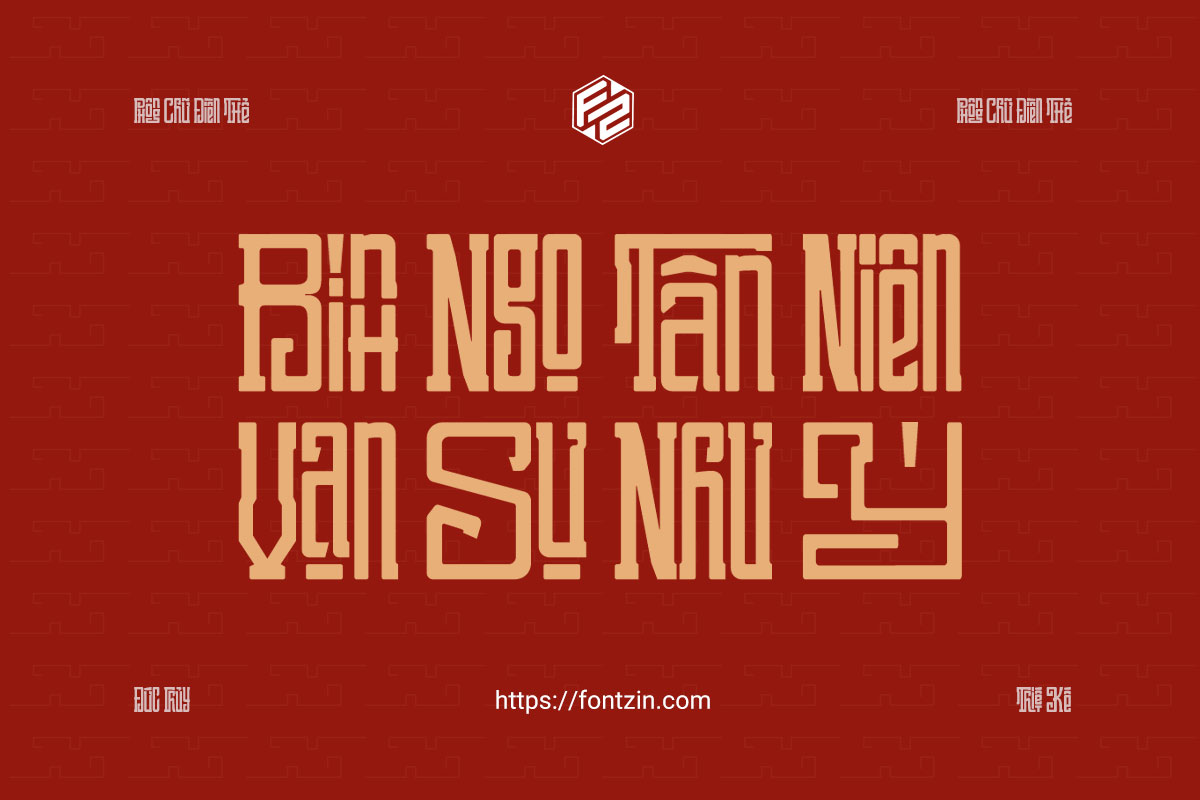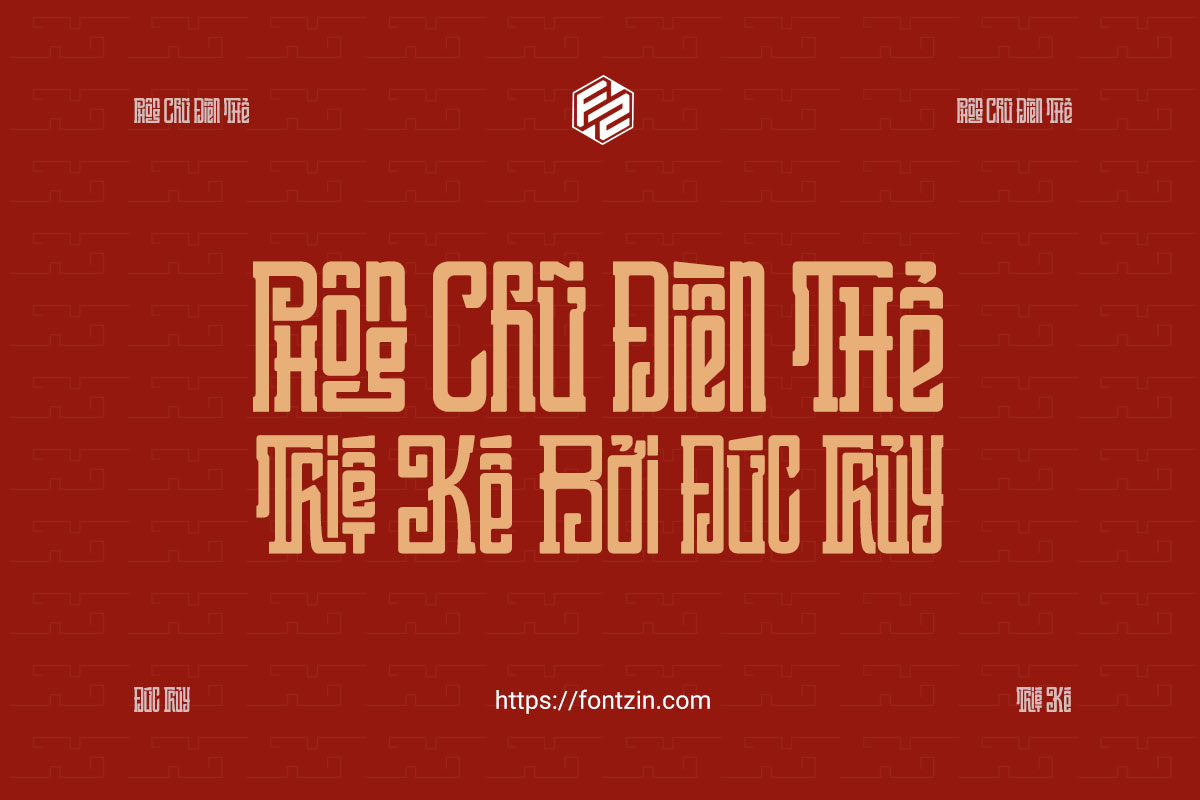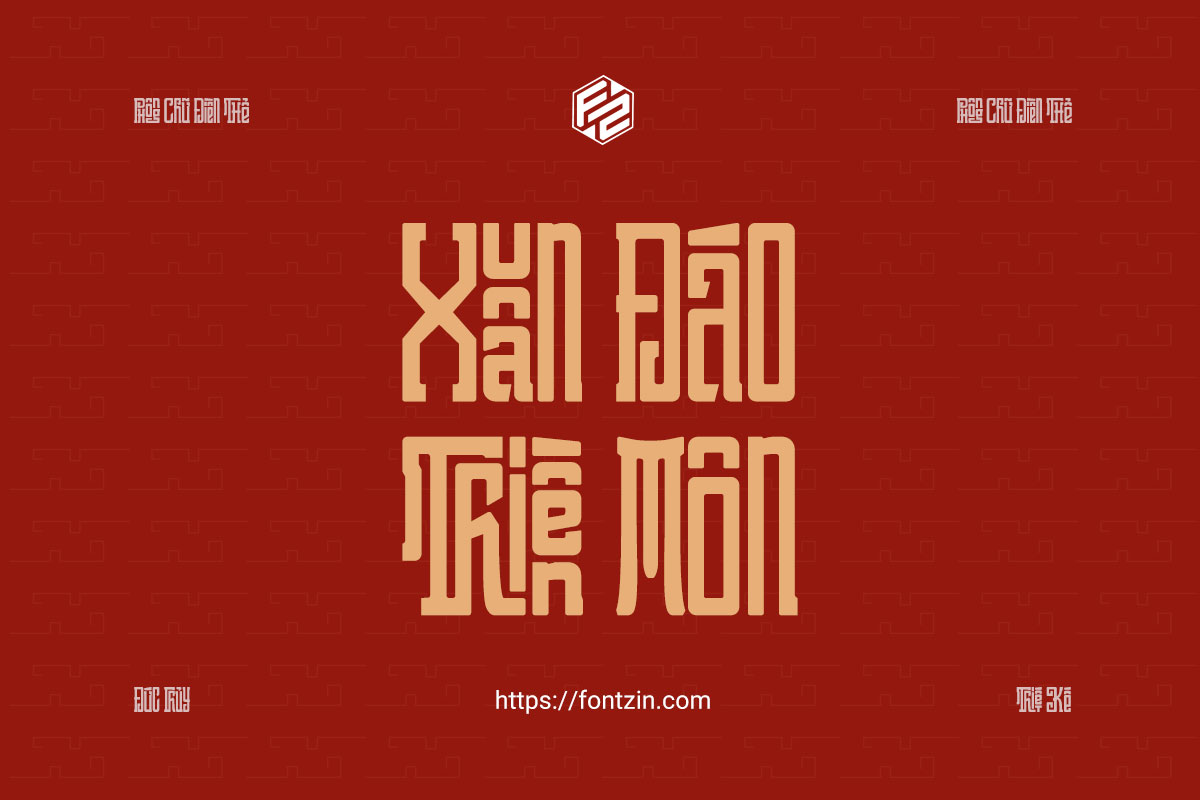
Font Điền Thể V8 (Font Triện) bao gồm gần 10.000 chữ Tiếng Việt mô phỏng phong cách chữ viết Trung Hoa, mỗi ký tự được sắp xếp gọn gàng trong một ô vuông với nét chữ chỉn chu, độc đáo.
Phiên bản Điền Thể Tiếng Việt được FontZin nghiên cứu và phát triển với cách sắp xếp logic, dễ đọc, dễ nhận dạng, đồng thời vẫn giữ được giá trị văn hóa truyền thống mà vẫn có tính sáng tạo.
Ứng dụng font điền thể
Font Điền Thể đặc biệt phù hợp cho các ứng dụng như thiết kế đình chùa, nhà thờ, kinh Phật, sớ, câu đối, ấn triện, triện vuông, khắc dấu tên và các ấn phẩm mang yếu tố tâm linh – cổ truyền. Font hỗ trợ gõ Tiếng Việt chuẩn Unicode (Telex), cho phép copy–paste, sử dụng linh hoạt trên máy tính và thiết bị di động, đáp ứng tốt cả nhu cầu thiết kế và ứng dụng thực tế.
Font Điền Thể FontZin là lựa chọn chuyên biệt cho những ai đang tìm kiếm một kiểu chữ triện Tiếng Việt vừa chuẩn mực, vừa mang dấu ấn nghệ thuật độc quyền.